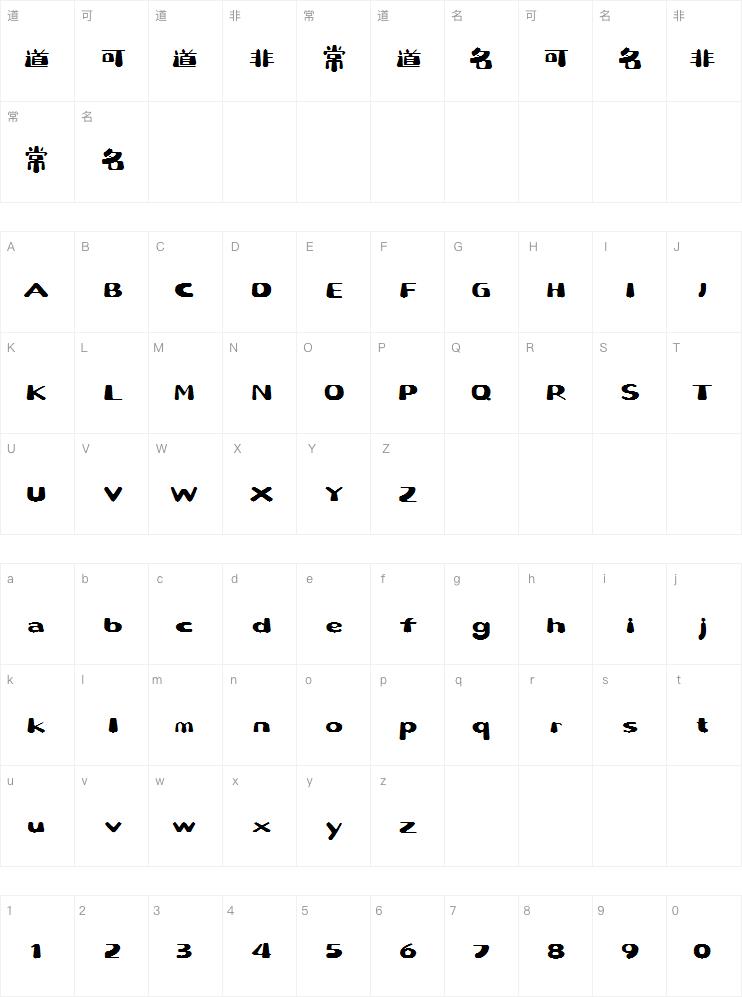
上首图图体
上首图图
上首图图体,简体中文约6763字,在笔画设计上,充满了巧思与变化。笔画有粗有细,粗的部分好似坚实的根基,传递出一种稳重大气的力量感,细的部分则宛如灵动的丝线,为字体增添了丝丝轻盈与活泼,粗细之间的转换自然流畅,使得字体在视觉上既有刚劲有力的一面,又不会显得笨拙沉闷。使得字体在具备典雅端庄气质的同时,又洋溢着满满的童趣与俏皮,极具现代创意字体的独特韵味,从而能够广泛应用于众多场景之中。适用于搭配标志、广告标语、商业广告等高端属性。
上首图图体